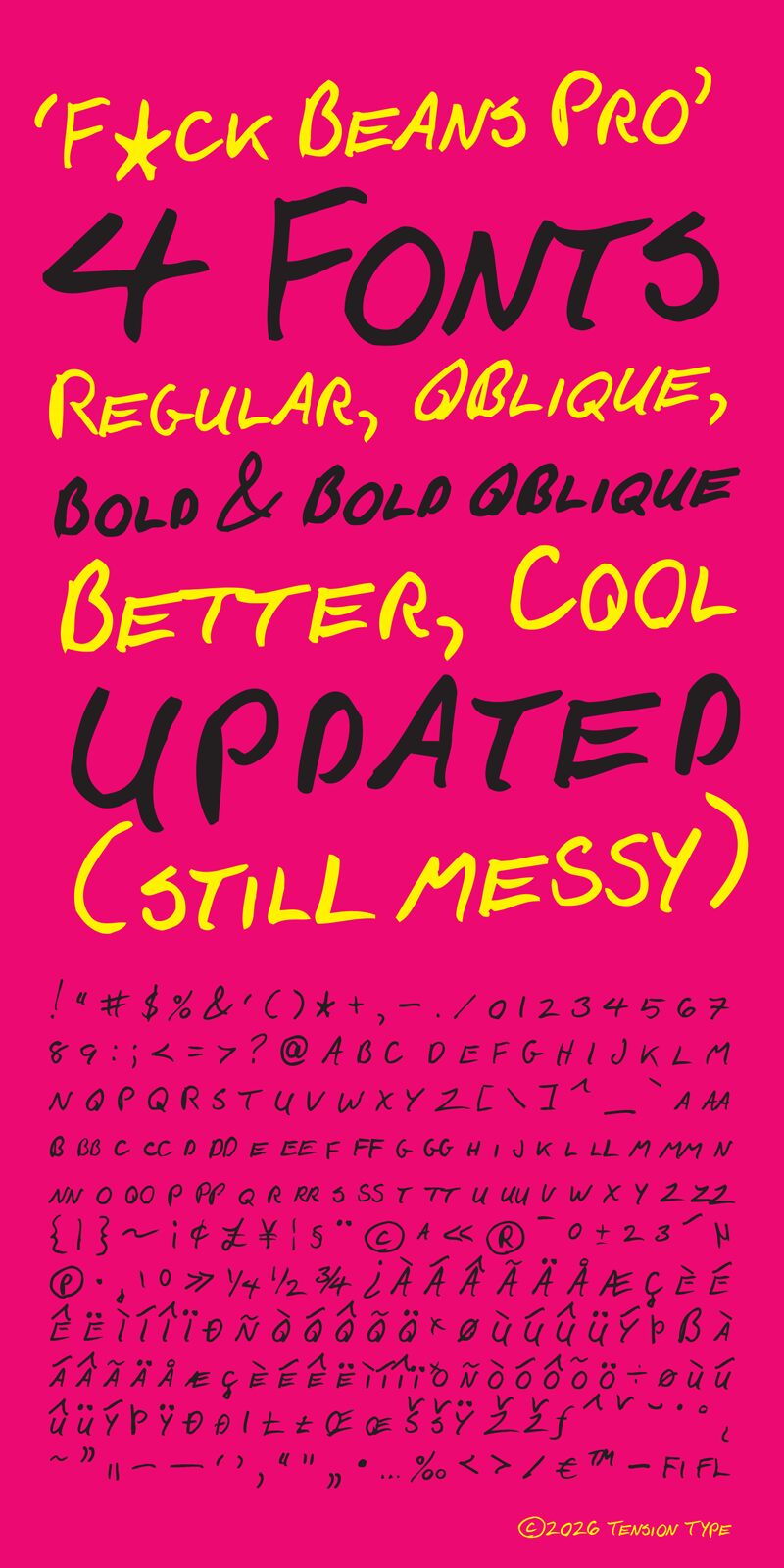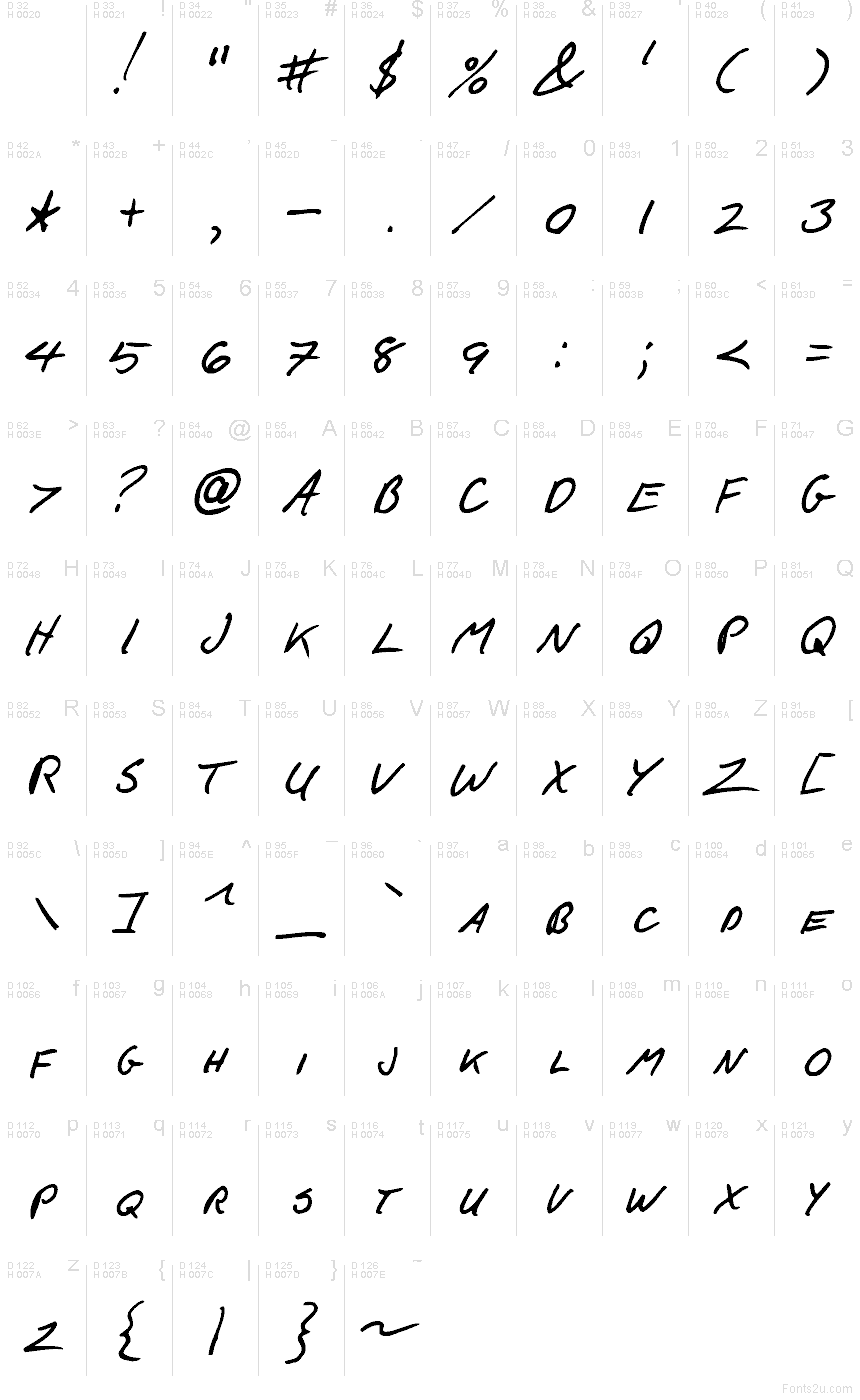
Fuck Beans Pro Oblique est une police manuscrite inclinée gratuite de 2026, au rythme vif et façon pinceau. Les lettres semblent tracées d'un seul jet : des traits larges et légèrement irréguliers, des courbes douces et une inclinaison décontractée vers la droite lui donnent le ton d'une note audacieuse griffonnée dans un carnet de croquis ou sur une affiche.
Ce côté informel en fait un choix naturel pour des visuels musicaux, des couvertures de fanzines, des graphismes streetwear, des titres d'affiches et des cartons de titre où le message doit paraître immédiat plutôt que soigné. En tant que police gratuite, elle fonctionne aussi très bien pour des visuels réseaux sociaux et des annotations de packaging, surtout quand vous recherchez une empreinte humaine brute plutôt qu'une écriture trop propre.
Cette police est basée sur l'écriture manuscrite d'un vieil ami. Je l'ai créée il y a longtemps, alors que j'apprenais à utiliser Fontlab 5. Je l'ai mise à jour depuis et je continue d'apprendre.
This is an old friend of mines handwriting. I created it a long time ago when I was learing how to use Fontlab 5. This is an update I have done. Still learning, but this version is definately an improvement.